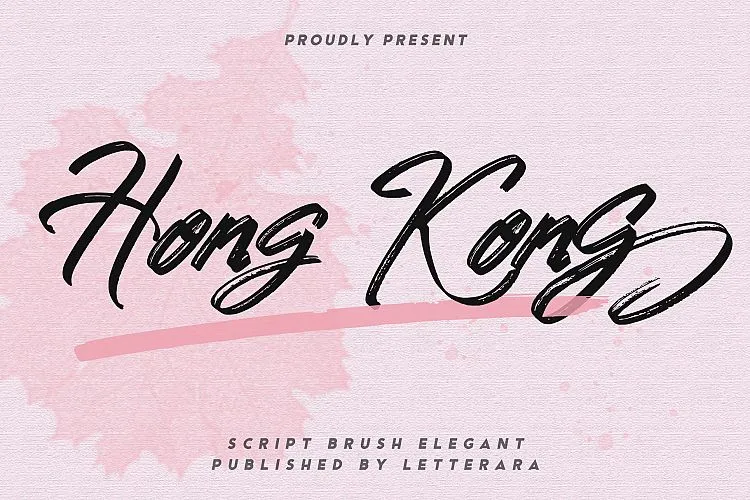
Hong Kong Brush Font – Download Grátis
A Hong Kong Brush Font é uma excelente escolha para designers que buscam dar uma aparência elegante e masculina a seus projetos. Ela é um desenho à mão livre feito com canetas, ideal para criar design inovador devido à sua riqueza de detalhes e linhas finas aparentes. Esta fonte tem versões tanto maiúsculas quanto minúsculas, além de ligatures que a tornam ainda mais versátil. A Hong Kong Font também apresenta um toque único em cada letra, o que é especialmente notável em sua aparência elegante. Ela pode ser usada não apenas para projetos tradicionais como logotipos e embalagens de produtos, mas também para elementos de moda como roupas e acessórios. A Hong Kong Font enriquecerá qualquer design, seja para uma lembrança de casamento, um vídeo ou até mesmo em embalagens de produtos. Para tornar seu projeto ainda mais chamativo, a Hong Kong Font inclui detalhes aparentes nos traços rápidos e nas partes finas da letra. É perfeita tanto para eventos como casamentos e festas de Natal, quanto para criação de logotipos modernos ou slogans emocionantes para sua marca online. Com uma variedade de usos, a Hong Kong Font é certamente a escolha ideal para qualquer projeto que precise de um boost no design tipográfico e deseje ter uma aparência única na tela do usuário.